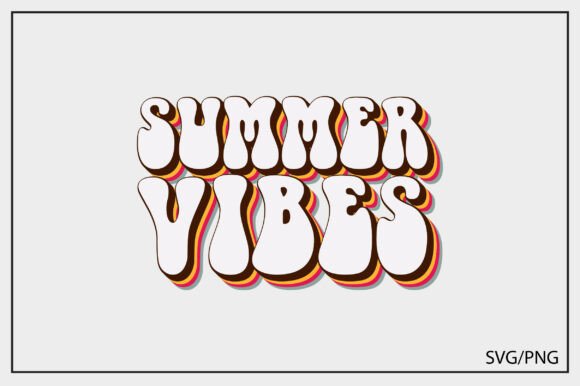
Summer Vibes Retro Font Typography
Om du letar efter högkvalitativa tillgångar som Summer Vibes Retro Font Typography, är detta premiumpaket ett fantastiskt val för dina kreativa projekt.
Oavsett om du skapar POD-produkter (Print on Demand), bröllopsinbjudningar eller grafik för sociala medier, är Summer Vibes Retro Font Typography ett perfekt val.